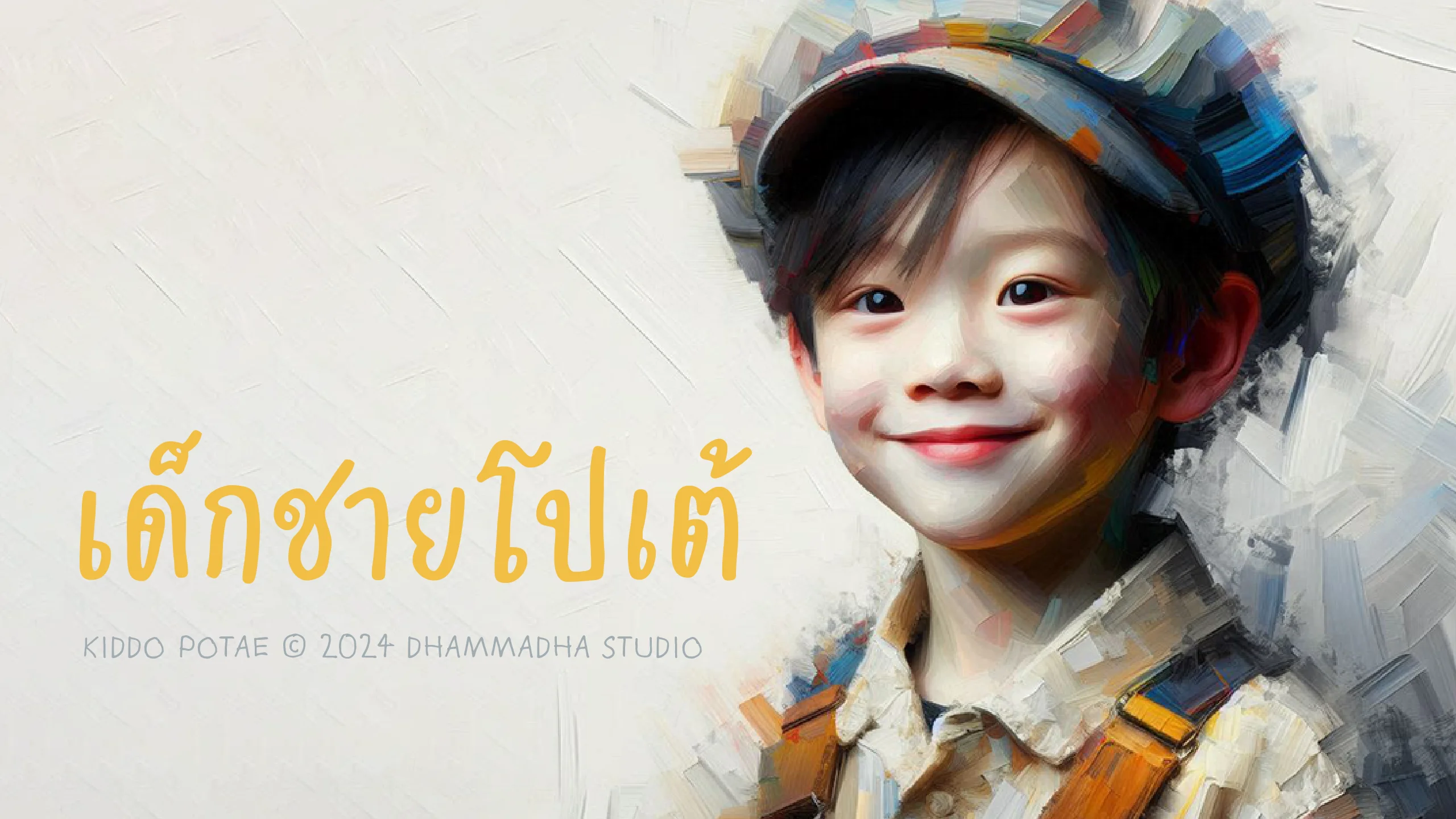
KIDDO POTAE
"เด็กชายโปเต้ | KIDDO POTAE" คือชุดอักษรลายมือเด็กที่ผ่านการรังสรรค์อย่างประณีตเพื่อให้เป็นฟอนต์ที่มีความครบถ้วนและสมบูรณ์แบบที่สุดชุดหนึ่ง โดยเราตั้งใจเก็บรักษาจังหวะการเขียนที่ดูเป็นธรรมชาติ ไร้เดียงสา และเต็มไปด้วยพลังของเด็กชายตัวน้อยเอาไว้อย่างครบถ้วน มอบบรรยากาศที่ดูมีชีวิตชีวา สนุกสนาน และแจ่มว้าวที่สุดในสยามประเทศ พร้อมที่จะเปลี่ยนทุกพื้นที่การสื่อสารให้กลายเป็นเรื่องราวที่น่ารักและเป็นกันเองอย่างถึงที่สุด เรายังได้ขยายขอบเขตการใช้งานให้ดูสมจริงขึ้นไปอีกขั้น ด้วยการเพิ่มชุดอักษรทางเลือกไว้มากถึง 3 รูปแบบ ซึ่งทำงานร่วมกับฟีเจอร์ Contextual Alternates (calt) ที่จะสลับสับเปลี่ยนตัวอักษรให้อัตโนมัติในขณะที่คุณพิมพ์ ทำให้มั่นใจได้ว่าแม้จะพิมพ์ด้วยข้อความเดิม แต่อักษรแต่ละตัวจะมีรูปลักษณ์ที่แตกต่างและไม่ซ้ำกัน มอบผลลัพธ์ที่ดูเหมือนการเขียนด้วยลายมือสดๆ อย่างเป็นธรรมชาติที่สุด เหมาะสำหรับงานออกแบบที่ต้องการความใกล้ชิดและเข้าถึงง่าย ไม่ว่าจะเป็นการทำคอนเทนต์สำหรับครอบครัว สื่อการเรียนรู้ งานกราฟิกที่ต้องการความขี้เล่นและดูโดดเด่นไม่ซ้ำใคร หรือแม้แต่การจัดวางพาดหัวที่อยากจะสร้างรอยยิ้มให้กับผู้อ่าน ฟอนต์ชุดนี้จะช่วยเติมเต็มจินตนาการและทำให้ทุกข้อความของคุณดูโดดเด่น มีสไตล์ และเปี่ยมด้วยเสน่ห์ของความเป็นเด็กอย่างสมบูรณ์แบบ ออกแบบโดย : Potae Khong-Udnun / Menee Khong-Udnun พัฒนาฟอนต์โดย : Montonn Thanaroj